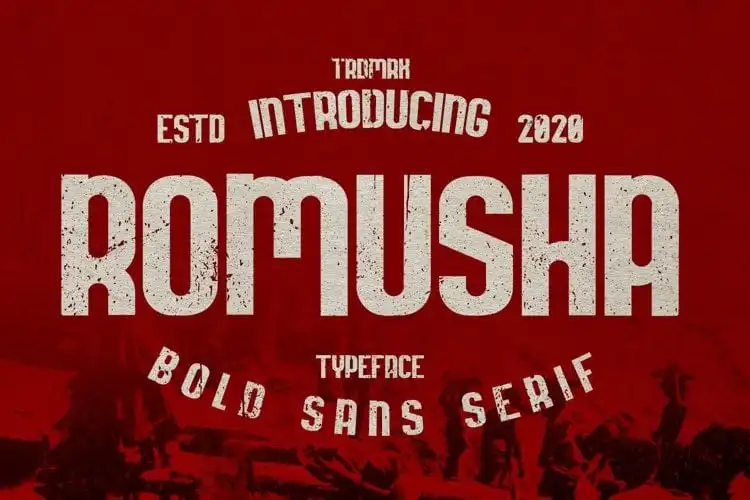
Romusha Display Font – Fonte Grátis
Romusha Display Font
Introduzimos a Romusha Display Font, uma tipografia sans-serif clássica com várias opções de estilo alternativos para escolha. Esta tipografia é robusta e simples, criada por JujunGag e compartilhada pela 99designs. Perfeita tanto para design de produtos como para o nome de um barbeiro, revistas, camisetas de iniciantes em escalada ou até mesmo seu próprio logotipo ou tipografia. Romusha Display é uma fonte especializada com uma inspiração e jogos de humor incríveis que podem aprimorar qualquer projeto criativo.